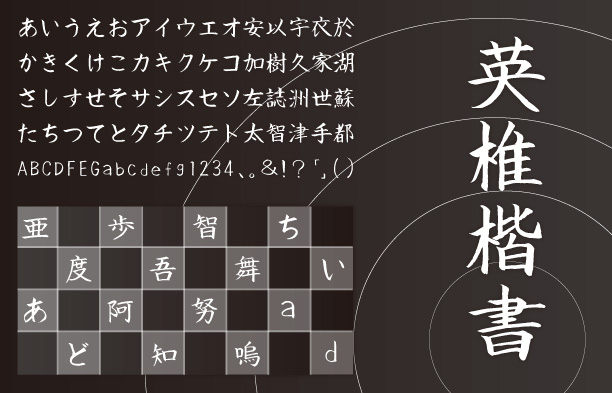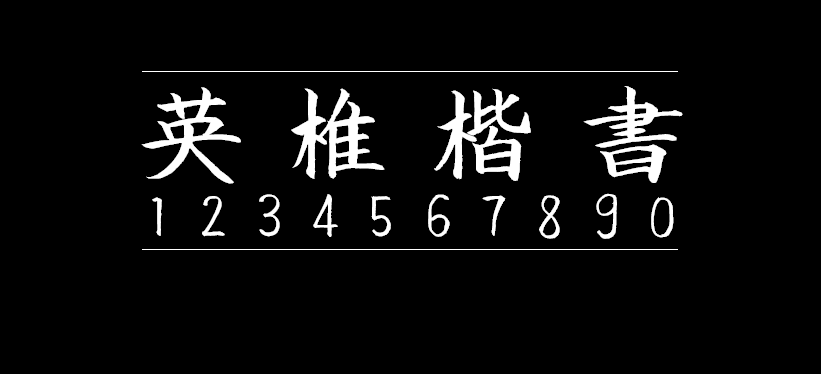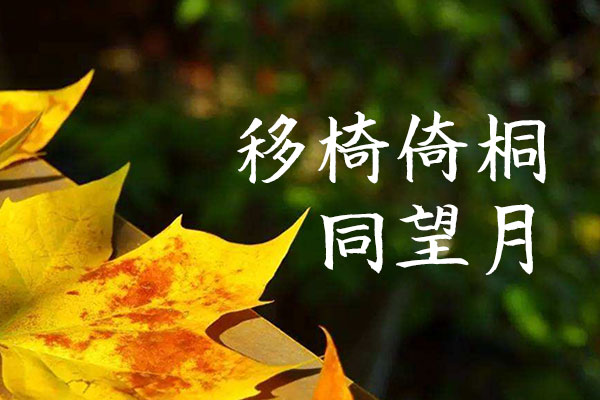
英椎楷书
英椎楷书(英椎楷書 ackaisyo)是日本acfont自己手写开发的一款字体,这款字体端庄雄伟,书写工整,是一款十分好看的手写字体。英椎楷书共收录了6879个文字,因为日文字符一般是以JIS水准为标准,所以虽然是日文字体,但是中文繁体支持得还是比较完整的。而简体中文则相对较少,不过也确实是一款挺好看的书法字体。喜欢的朋友赶紧下载吧! 英椎楷书作者已经公开声明这款字体可以免费商用,所以大家放心使用吧!